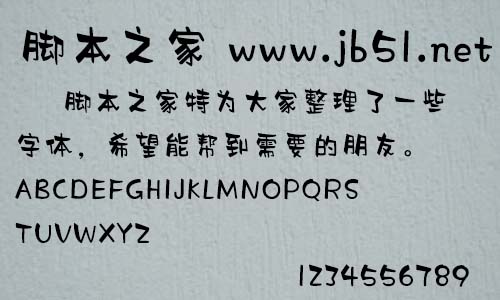
方正馬克體簡(jiǎn)一款由方正字庫(kù)出品的藝術(shù)字體,字體筆觸較為粗實(shí),書(shū)寫(xiě)俏皮可愛(ài),具有很好的視覺(jué)感,適合應(yīng)用于藝術(shù)設(shè)計(jì)、平面宣傳設(shè)計(jì)、網(wǎng)頁(yè)設(shè)計(jì),書(shū)法字帖等領(lǐng)域。
方正馬克體是一款融合了手繪POP的創(chuàng)意字體。書(shū)寫(xiě)果斷,充滿活力,意趣十足。整體風(fēng)格新穎可愛(ài),特色鮮明。適用于餐飲類(lèi)產(chǎn)品包裝設(shè)計(jì),商業(yè)類(lèi)趣味廣告和新媒體宣傳設(shè)計(jì)。